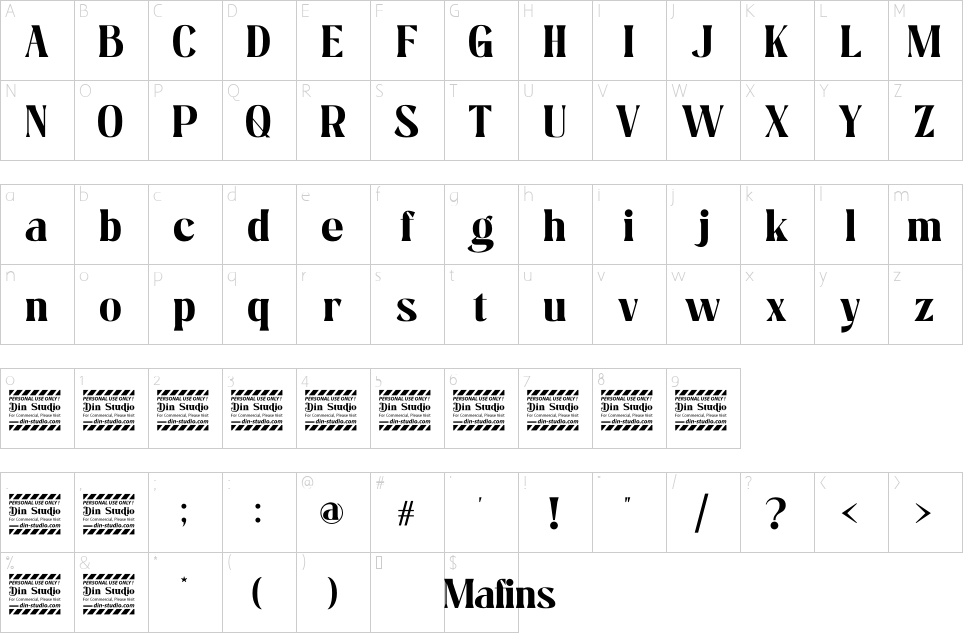
Mafins é uma elegante e sofisticada fonte gráfica que adicionará um toque especial a seus projetos digitais. Desenvolvida pelo designer Natha Type, Mafins oferece uma combinação de elegância e facilidade de uso, ideal tanto para criações digitais quanto para design gráfico. Com seu design minimalista e arredondado, ela se adequa perfeitamente a múltiplas aplicações, desde logotipos e marcas até design editorial e materiais de apresentação. Mafins é uma escolha ótima para quem busca uma fonte que seja tanto funcional quanto bonita, garantindo um visual profissional e atraente. Se você está procurando por um design gráfico cuidadosamente elaborado que você pode usar livremente, Mafins é uma fonte perfeita para você. Descarregada 1.727 vezes, a comunidade já testou e aprovou o trabalho incansável do designer Natha Type. Descarregue Mafins agora e dê vida a seus projetos digitais.